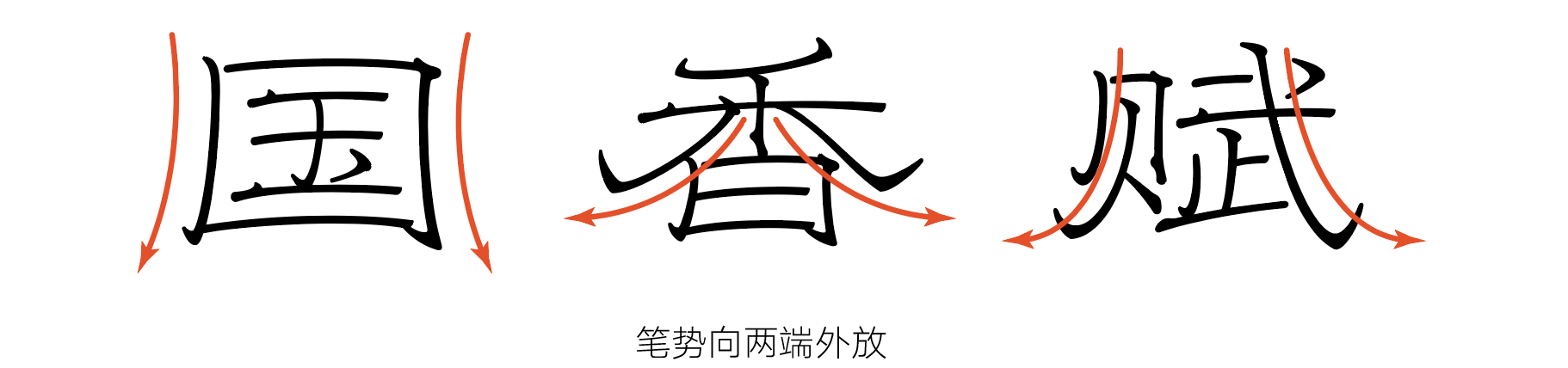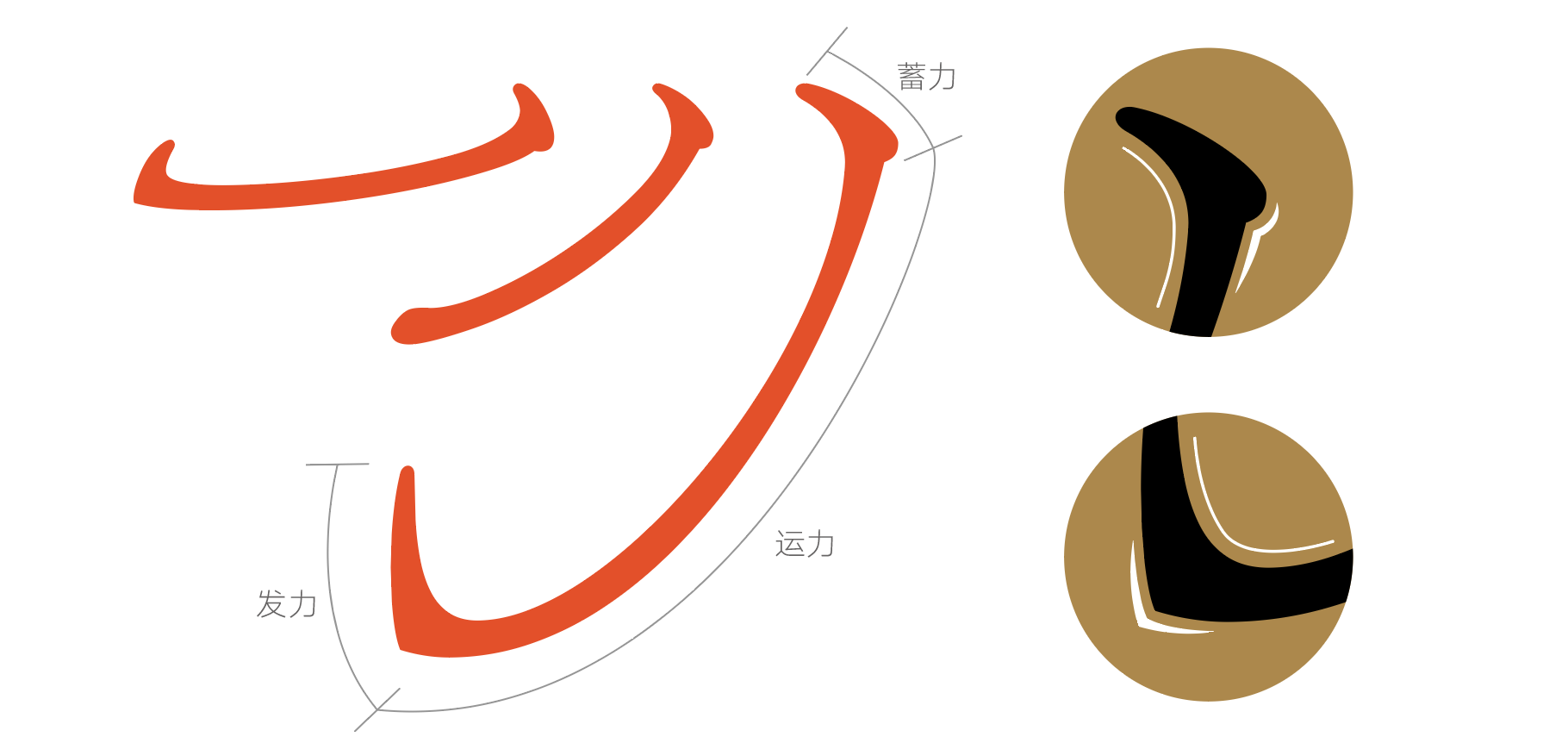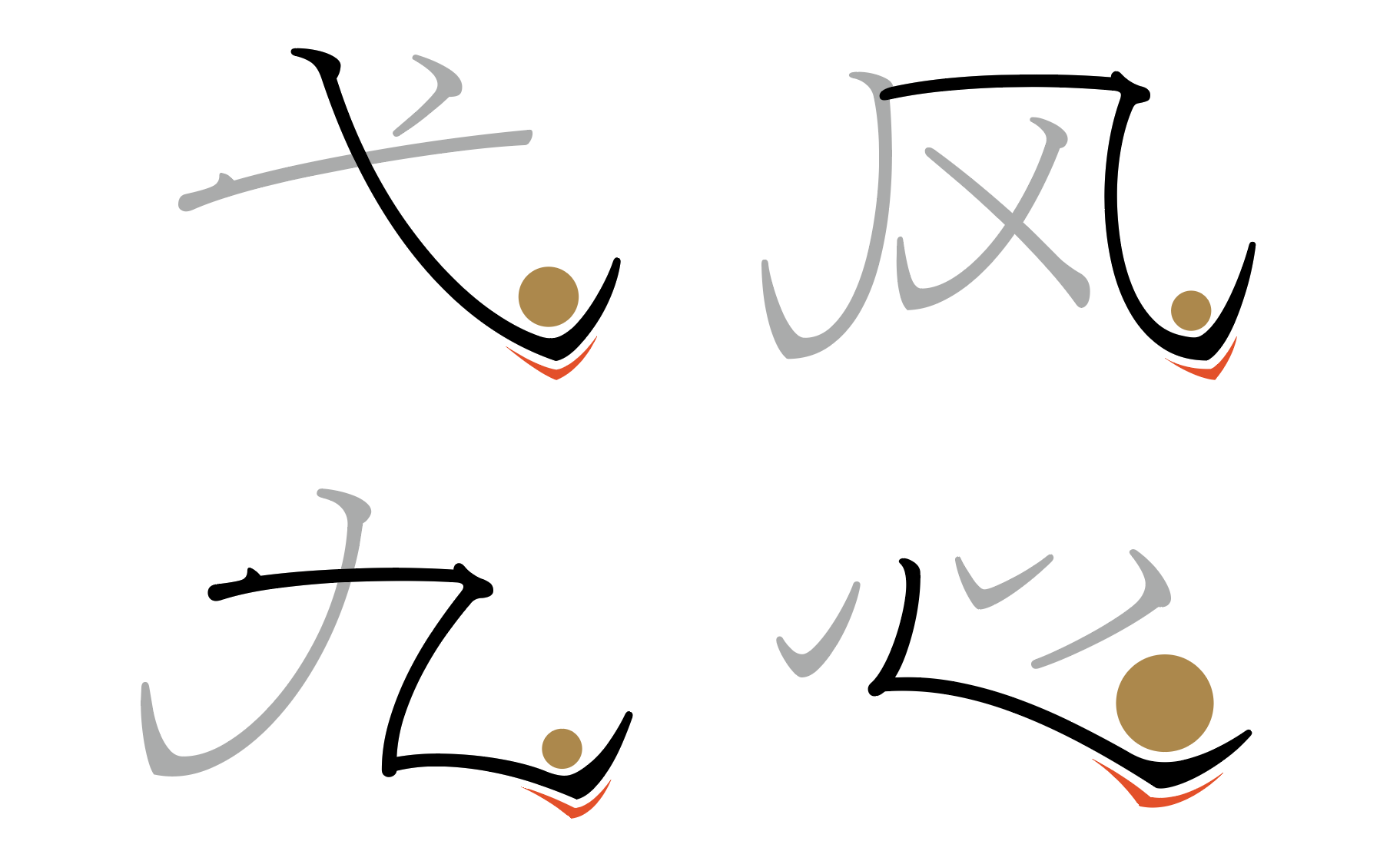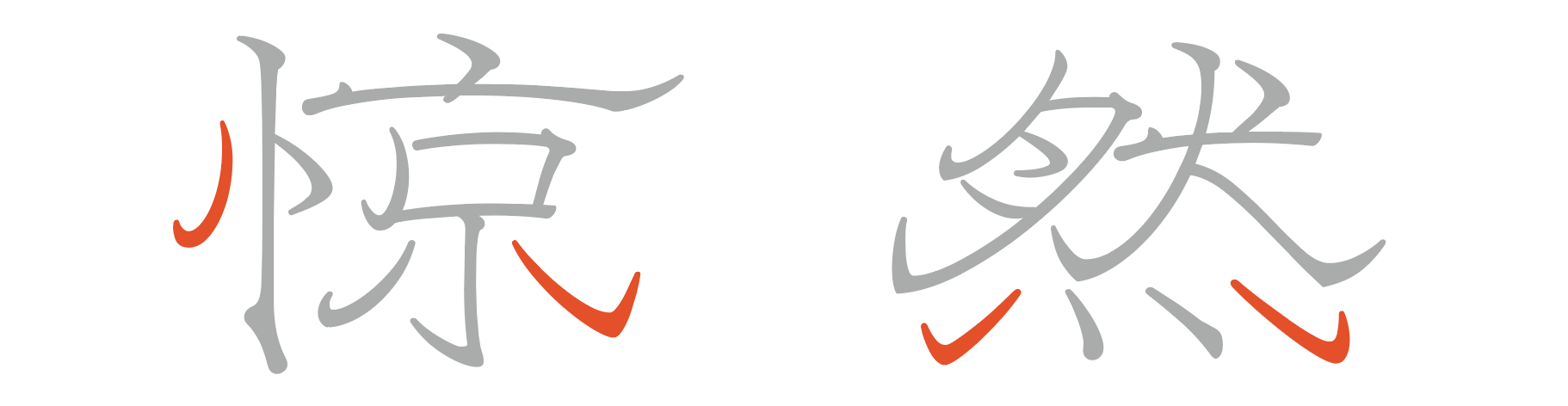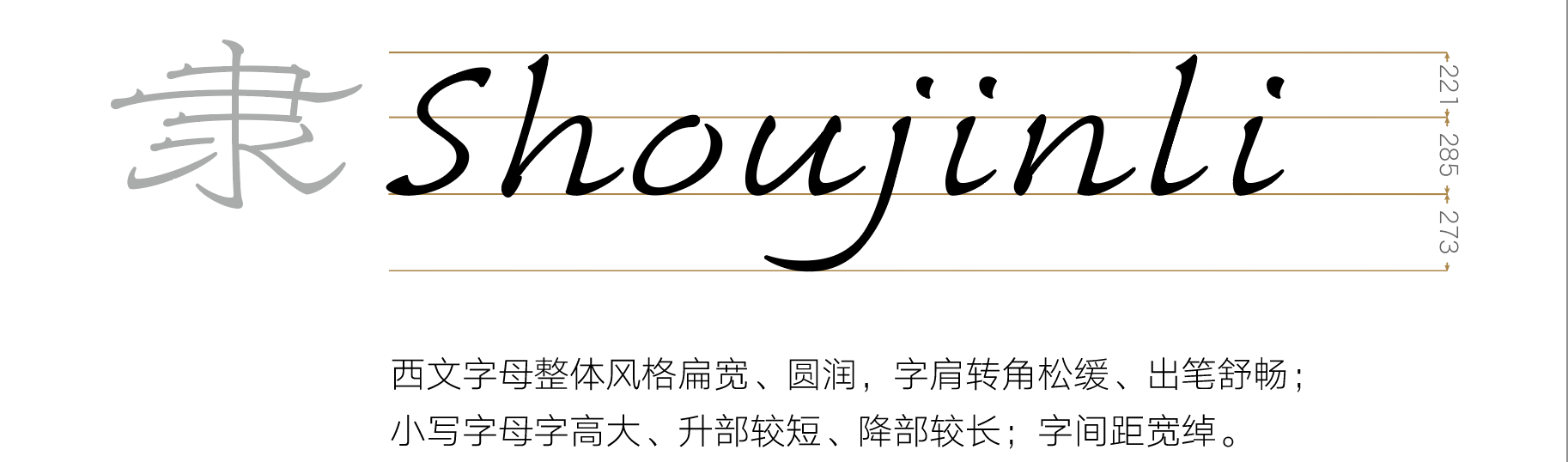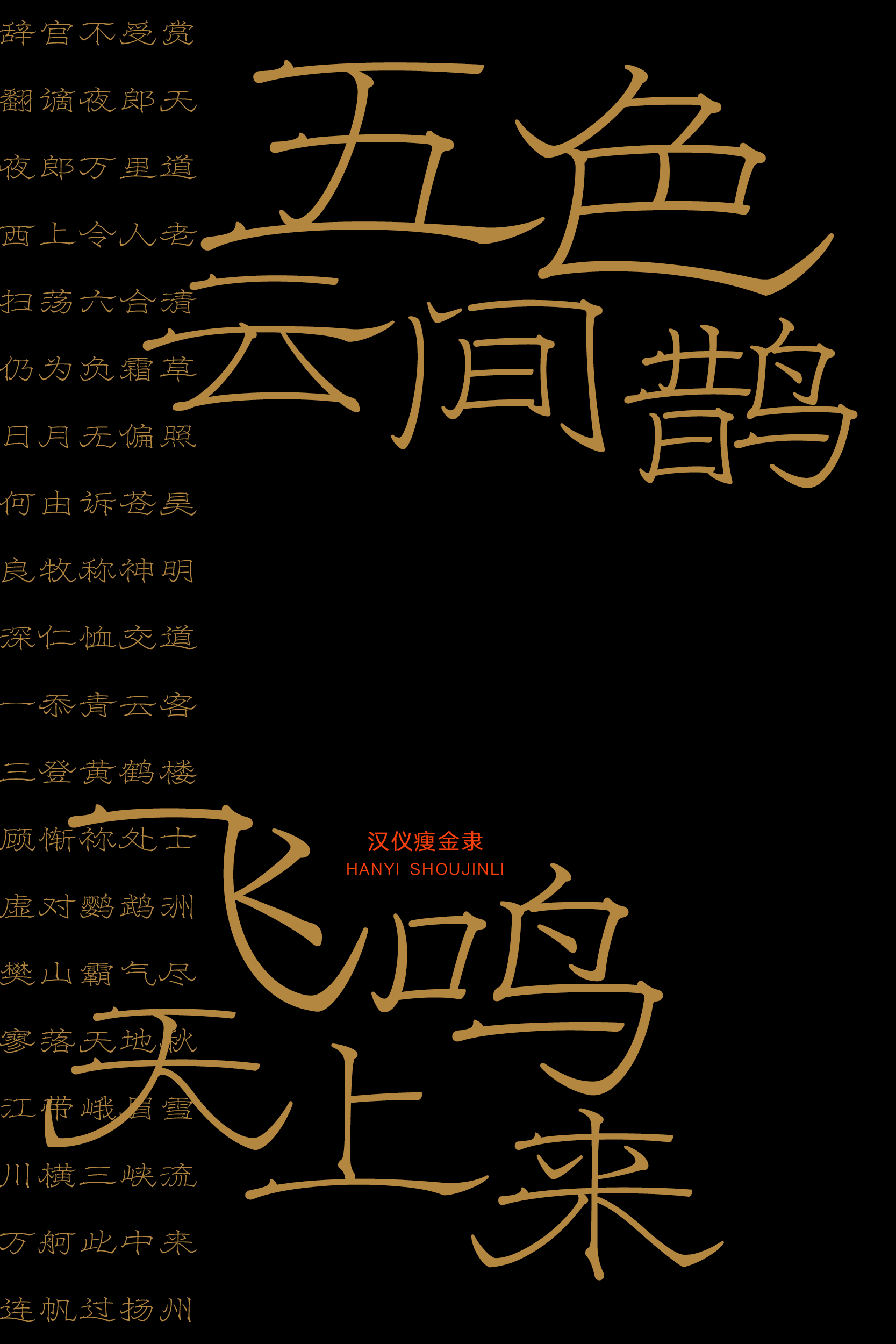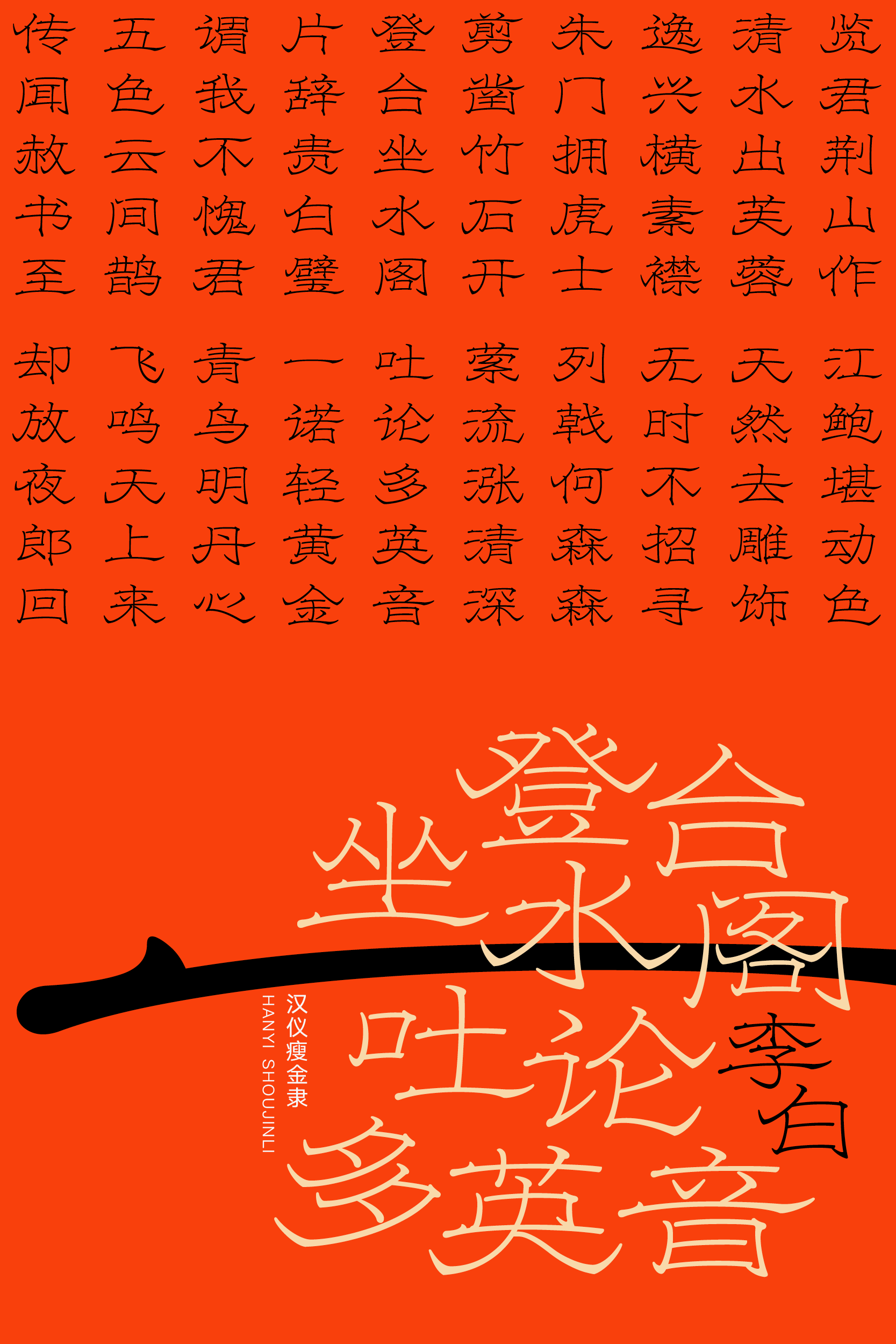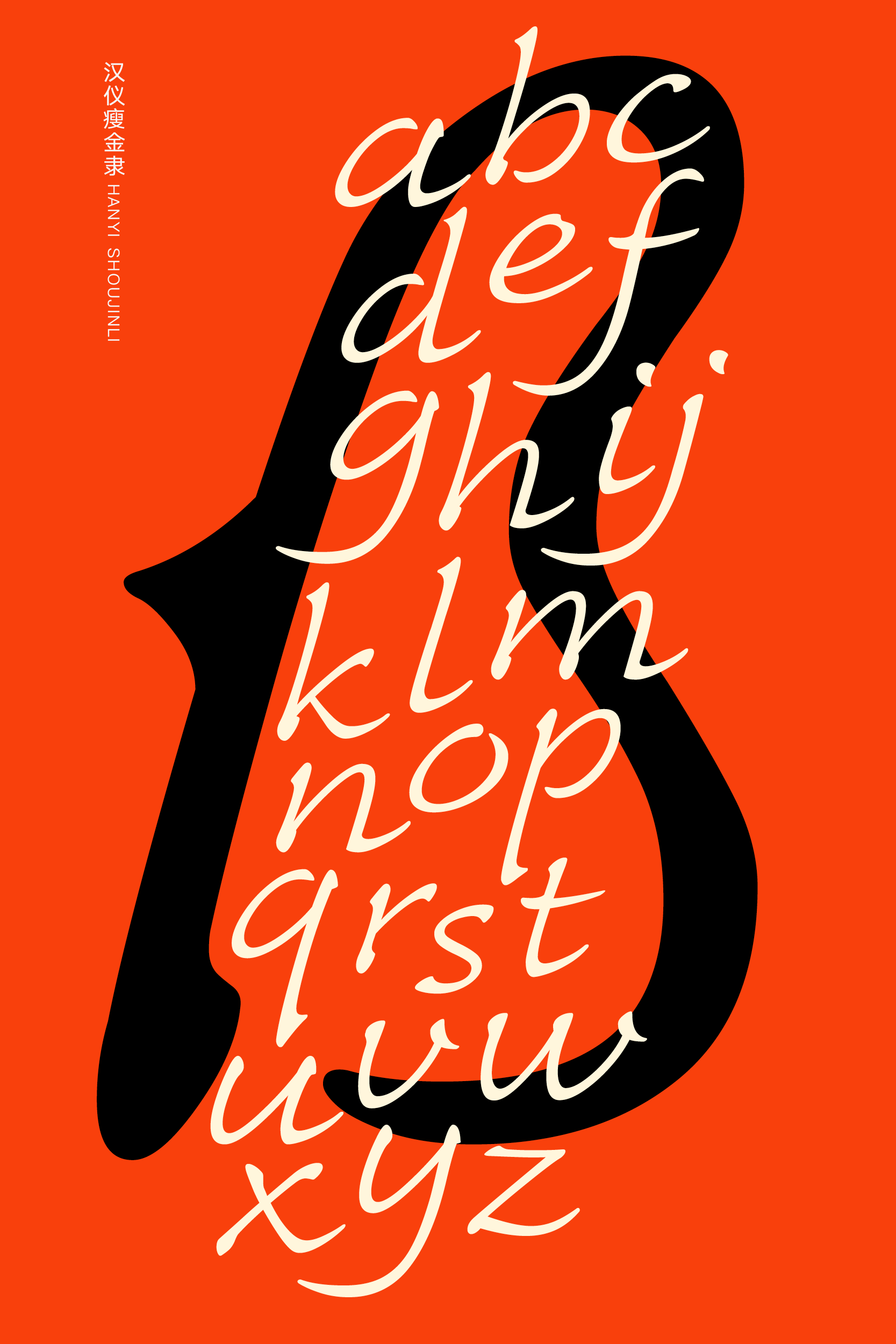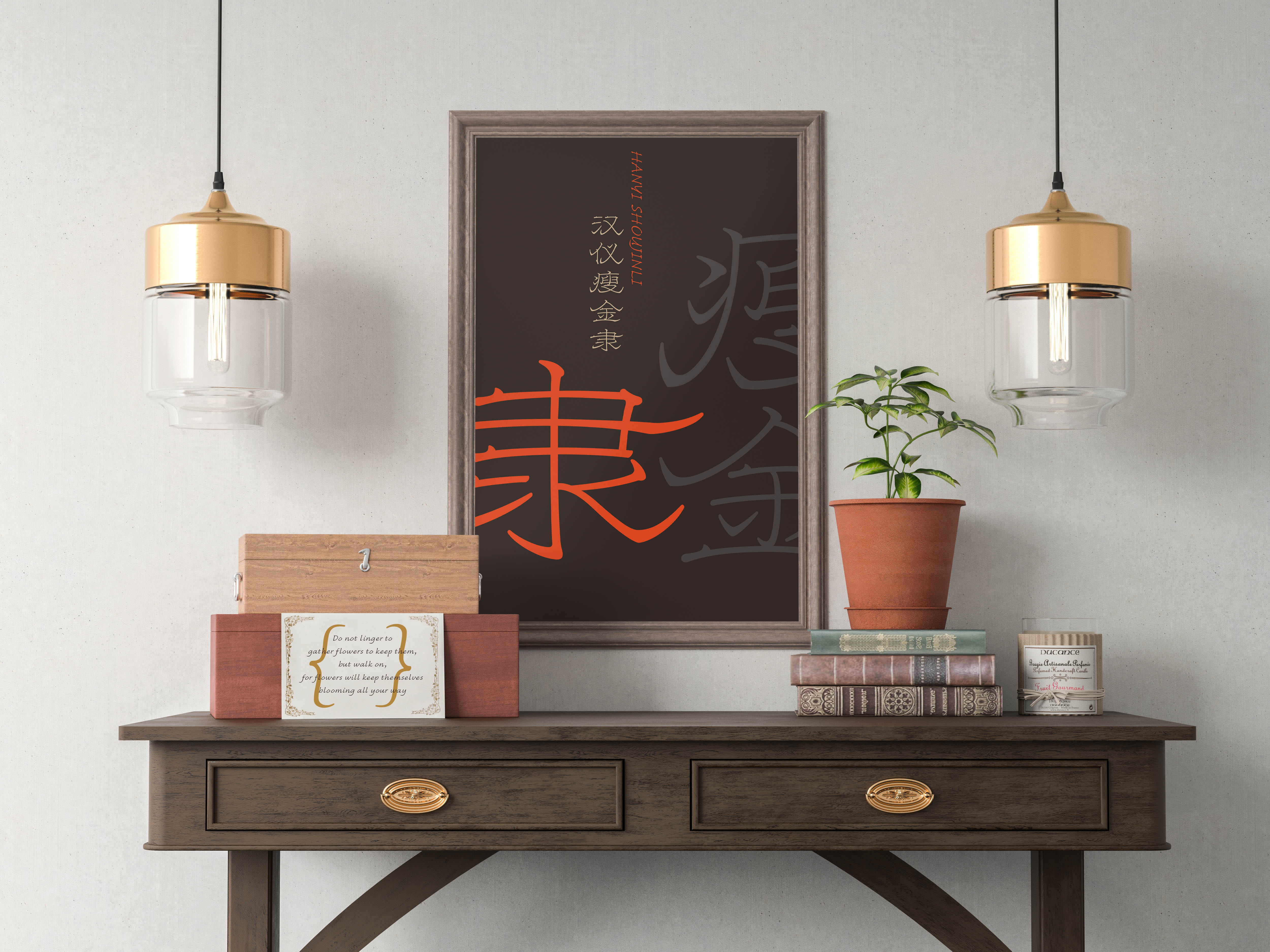
汉仪瘦金隶字体介绍,一款玲珑细腻,富艳精工的瘦金隶
复古 / 张扬 / 国风 / 雅致 / 浪漫 / 潇洒
汉仪瘦金隶|整体特点
汉仪瘦金隶是一款结合了瘦金书和隶书两者特征的创意设计字体,由汉仪签约设计师郭永祥设计。这款字结构参考隶书,造型扁宽,笔画排布均匀、笔势朝左右两侧伸展。笔画设计突出隶书特有的波磔和长掠造型,并吸取了瘦金书顿挫的用笔风格,使字形兼具隶书的华丽与瘦金书的遒美。该字体适合排布较短的文案,装点在作品中以渲染中式、华丽的氛围。
汉仪瘦金隶斩获国际知名字体设计大赛 Granshan 第 12 届 非拉丁字体组二等奖。
汉仪瘦金隶|字形特点
汉仪瘦金隶结构扁宽、横向舒展,使字体看起来稳健平衡、松缓舒畅。中间行笔有波势俯仰,收尾有磔尾。在用笔上,方、圆、藏、露诸法俱备, 笔势飞动,姿态优美。
撇捺和横画向两侧舒展,其他笔画均匀穿插其中,使得字形看起来更加稳定。笔画收放自如,有如云间仙鹤,动则轻盈灵秀,静又不失端雅雍容之象。
汉仪瘦金隶|笔画特点
汉仪瘦金隶较细的笔画使字面空间留白居多。夸饰的起收笔、折笔特征突出且丰富多变,整个字体展现出玲珑细腻、雅致幽娴的气质。
横画特征是隶书的灵魂所在,作者在不同位置设计了不同形态的横画。根据书写的运笔方式,将横画分出蓄力、运力、引而不发或发力挑出等几个阶段。
直竖起笔蓄力,收笔发力内敛,借鉴了瘦金书的提按和顿笔。撇竖的起收笔都较为内敛,具有撇的特征和竖的作用。
撇画同样借鉴瘦金笔法,曲线刚柔并济,起笔处有圆有方,以圆为主。
捺画的起笔部分低调简约,或简单地提示书写动作,或是直接露锋入笔。收笔的转折处也是外方内圆的设计方式。
弯钩、卧钩戈钩运用隶书处理方式,化圆为方。造型夸大有张力、契合整体风格。
该字体吸收了八分书的一部分特点,一些点画设计成撇和捺,以增加字体左右舒展感。
汉仪瘦金隶|中西文匹配
汉仪瘦金隶的西文设计带有手写签名风格,在钢笔的书写方式中加入软笔的特征去呼应中文设计。书写富有弹性,收尾处的笔锋特征明显。较圆润的笔画和转角显得书写速度略慢,笔画间的起笔收笔有顿笔的感觉,并在一些字母上做了断笔处理,保留手写的韵味。字母出笔能展现书写笔势灵动的韵律感,在文字排版时字母之间有似连非连的手写效果,且与中文笔画夸张的装饰感匹配度强。
汉仪瘦金隶 |字体样张